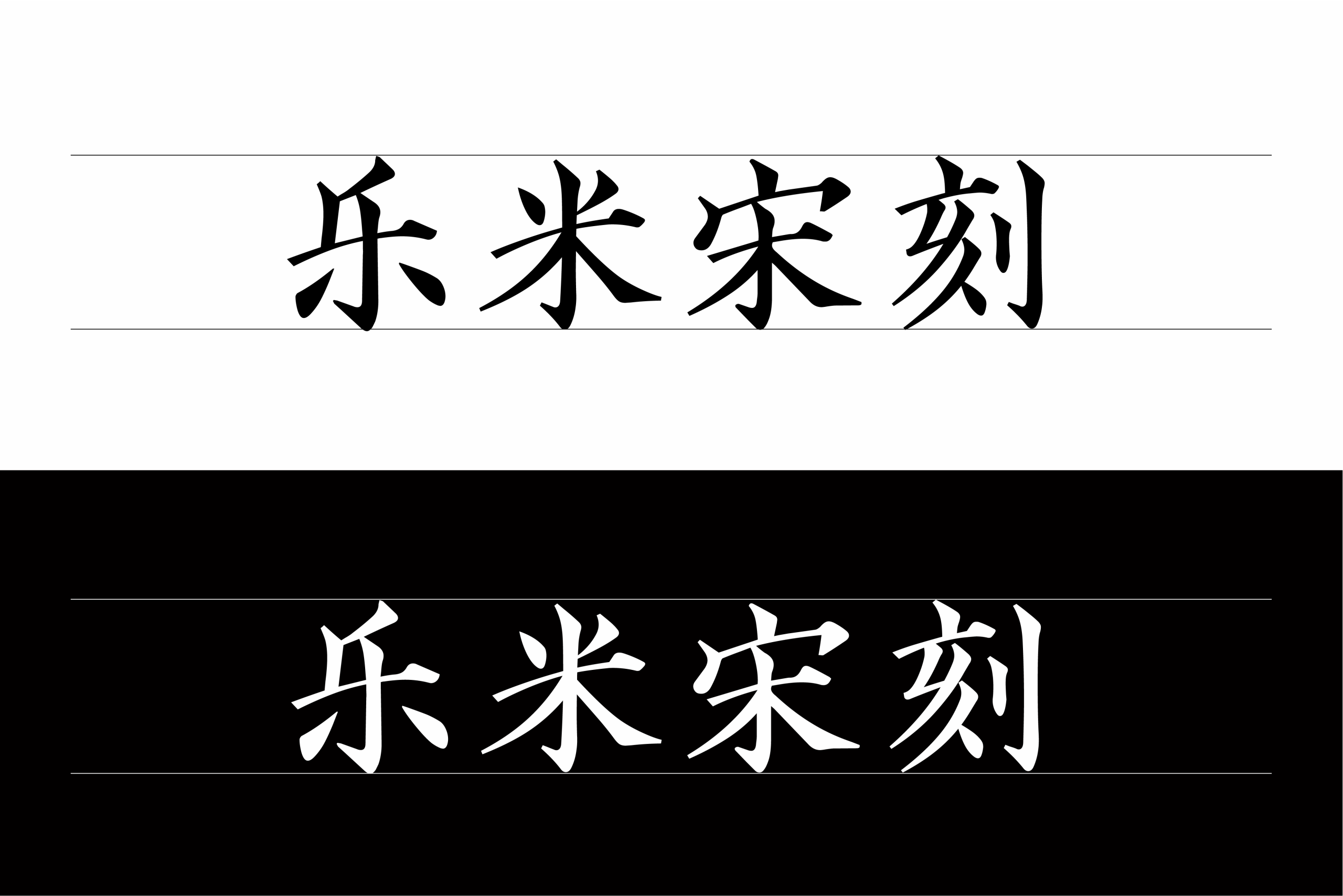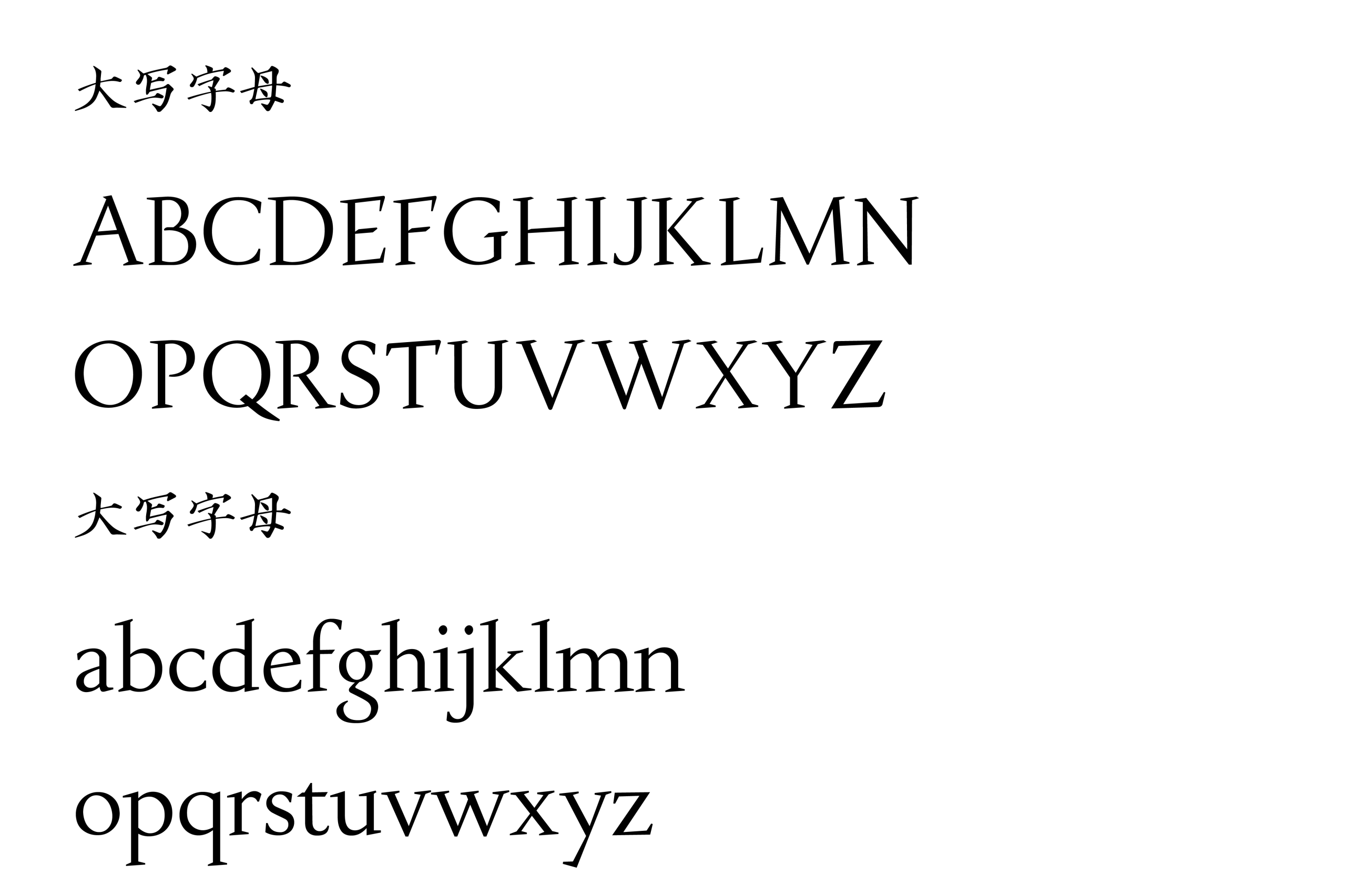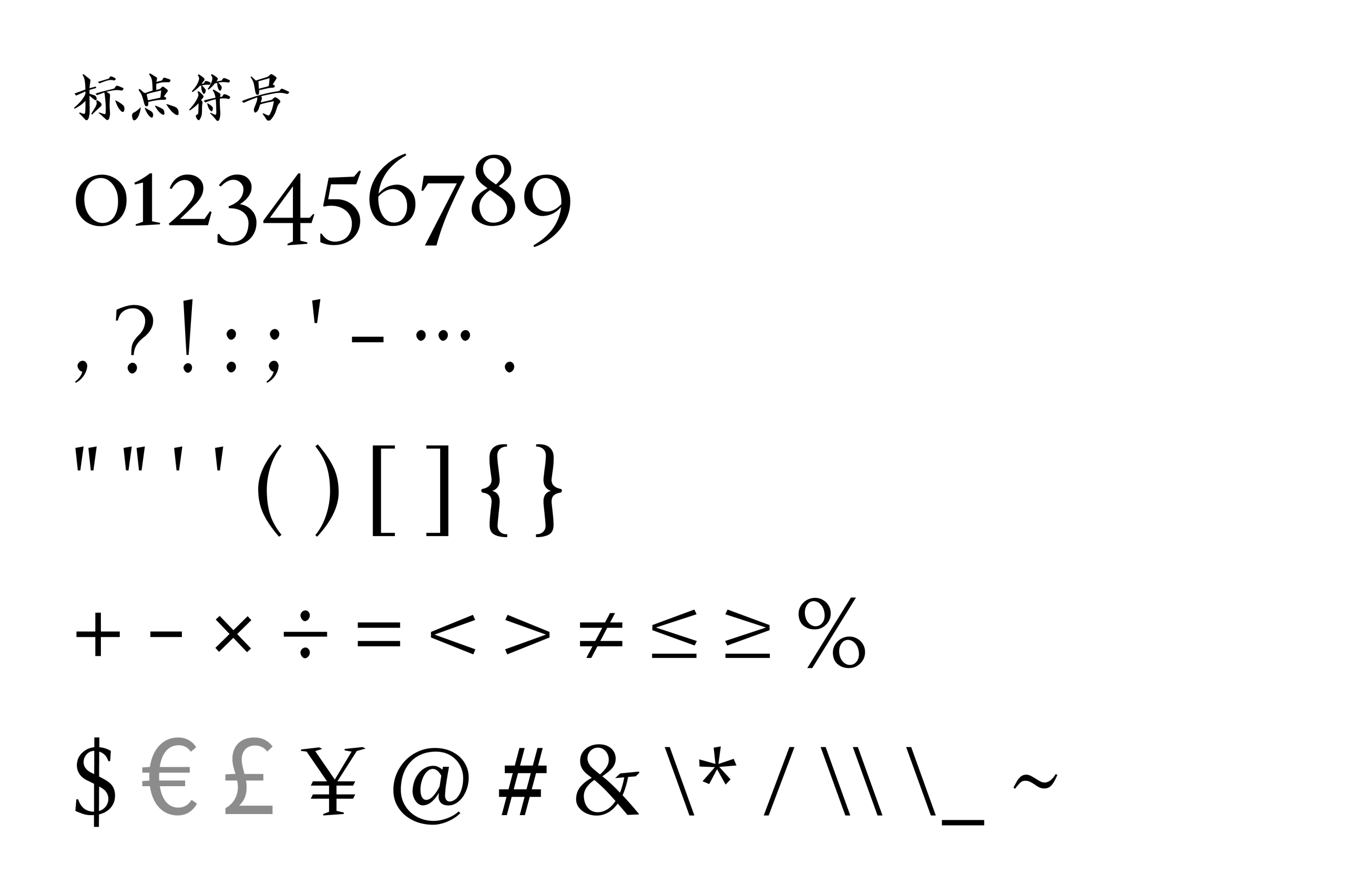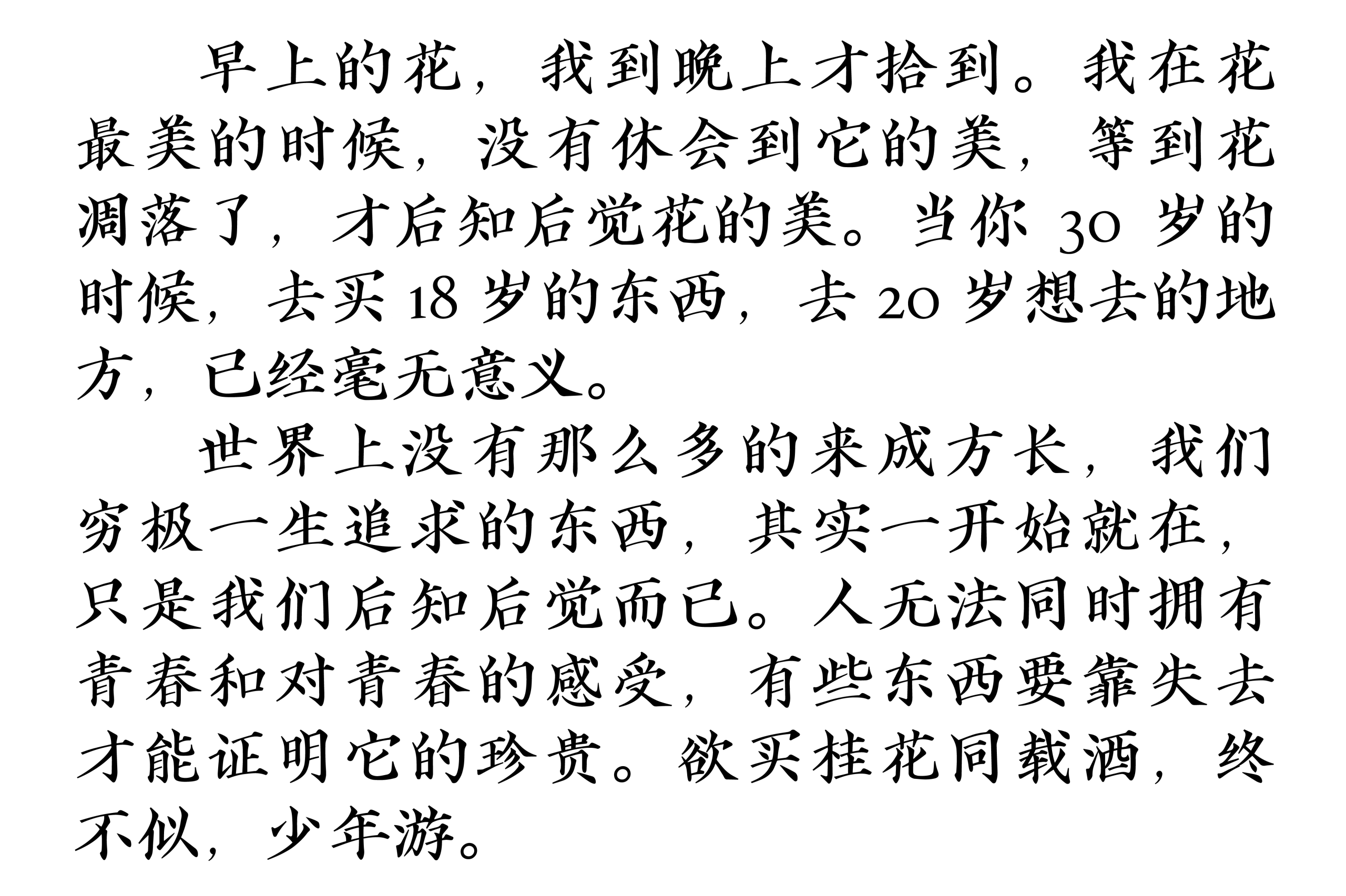
乐米宋刻
乐米宋刻体是一款由杭州乐米网络科技有限公司设计并发布的免费可商用中文字体。它以传统宋体结构为基础,融合了刻本字体的书写韵味与刀刻质感,整体气质古雅、清朗、克制,既保留了宋体字体端正稳重的阅读属性,又在笔画细节中呈现出更具人文感的东方审美。对于正在寻找免费商用中文字体、古风字体、宋刻体字体或适合文化类设计字体的用户来说,乐米宋刻体是一款兼具实用性与视觉辨识度的字体选择。
从字形表现来看,乐米宋刻体的中文部分具有清晰的宋体骨架,字形重心稳定,横竖关系分明,撇捺舒展自然。相比常规印刷宋体,它的笔画并不显得机械,而是在点画、转折、收笔等位置保留了类似手写与雕版刻印的细微变化,使字体看起来更有温度。无论是白底黑字还是黑底白字,乐米宋刻体都能呈现出较强的轮廓感和视觉张力,尤其适合用于标题设计、海报主视觉、书籍封面、文化宣传图以及品牌包装等需要突出字体气质的场景。
乐米宋刻体在大字号展示中表现尤为突出。字体笔画有明显的起伏变化,线条收放自然,既有古籍刻本的质朴感,也有现代字体设计所需要的规整度。用于国风海报、诗词排版、文创产品、茶叶包装、香氛品牌、传统节日视觉或文学类内容时,它能够快速建立起典雅、安静、富有书卷气的视觉氛围。同时,这款字体并没有过度装饰化,因此不会给设计带来过强的风格负担,在商业设计中具备较好的适配性。
从图文展示中的段落排版效果来看,乐米宋刻体也具备一定的正文可读性。较大的中文字面和稳定的字形结构,让它在短文、引言、诗句、摘录类内容中有较好的阅读体验。不过,由于字体本身带有较明显的宋刻笔意,小字号或长篇正文使用时需要注意行距、字距和字号控制。更推荐将乐米宋刻体用于标题、栏目名、章节标题、短句文案或重点内容呈现,正文部分可以搭配更中性的宋体或黑体,以获得更稳定的阅读效果。
除了中文字符外,乐米宋刻体还展示了英文大小写字母、数字、常用标点符号、数学符号和货币符号等内容。英文部分呈现出衬线体风格,与中文宋刻气质相对协调,适合用于品牌辅助文字、中英文混排标题、包装信息和视觉延展设计。数字和符号的设计也延续了字体整体的细长与古典感,使其在实际排版中不会显得突兀。
在应用场景上,乐米宋刻体适合文化艺术、出版阅读、品牌包装、新媒体设计和商业宣传等多个方向。它可以用于书籍封面、杂志标题、古风海报、诗词卡片、公众号头图、小红书封面、展览物料、文创周边、茶饮酒类包装、传统节日海报以及具有东方美学定位的品牌视觉系统。尤其是在需要表现“古典”“雅致”“书卷气”“东方感”“文学感”的设计项目中,乐米宋刻体能够提供较强的字体风格支持。
整体来看,乐米宋刻体是一款风格鲜明但不夸张的中文宋刻字体。它既有传统宋体的端庄与可读性,又通过笔画细节营造出古籍刻本般的文化气质。对于字库星球用户而言,如果需要一款免费商用、适合国风设计、文化视觉、出版标题和品牌包装的中文字体,乐米宋刻体值得收藏和尝试。